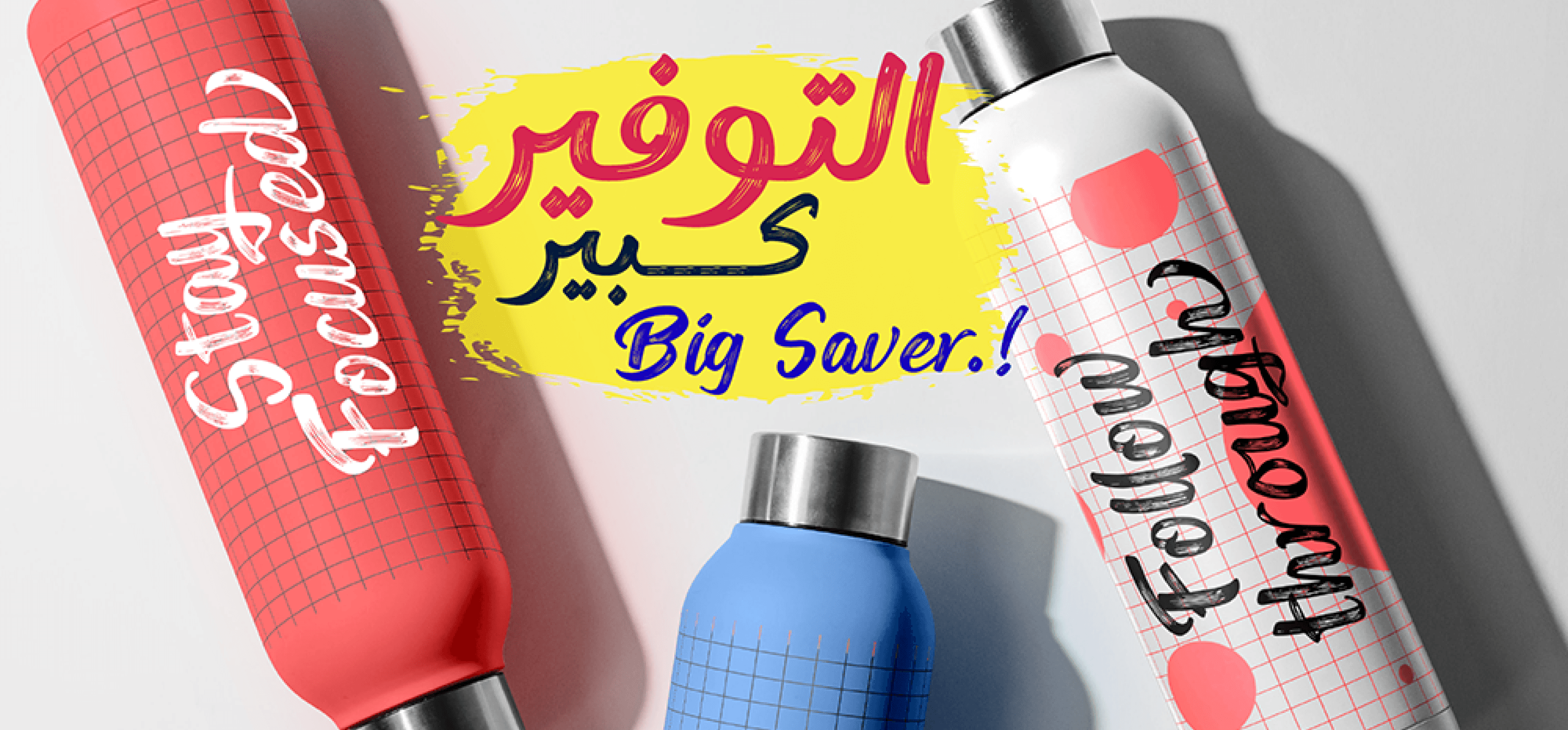
خط فرشاة الحبر – Ink Brush Arabic
خط عربي يجسد روح الكتابة اليدوية باستخدام تأثير الفرشاة، بتصميم انسيابي ومرن يمنح النصوص طابعًا عفويًا وحيويًا.
يتميز بحروف ناعمة ومتوازنة، ويُعد مثاليًا للمشاريع الإبداعية، مثل: التصاميم الطباعية، العبارات الملهمة، البوستات التفاعلية، والأعمال الفنية.
يدعم الخط الأحرف اللاتينية والعربية مع رموز متنوعة، ويُقدم مظهرًا جماليًا مناسبًا للشاشات والمطبوعات على حدٍ سواء.
مثالي للعناوين اليدوية، منشورات التواصل، وتصميمات الهوية ذات الطابع الشخصي.